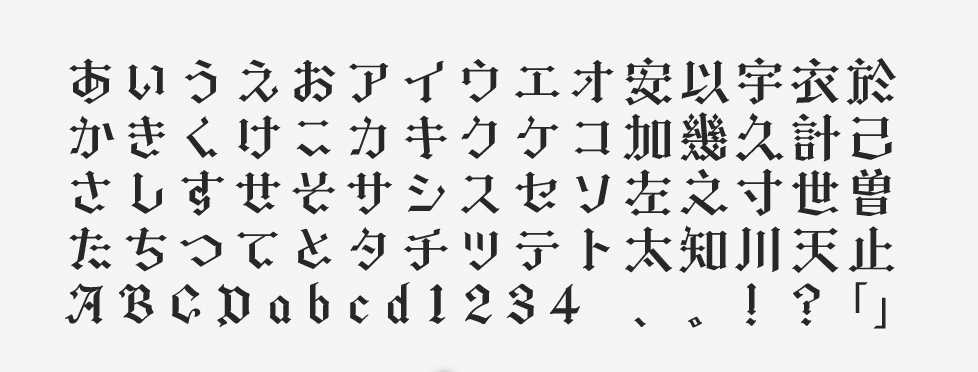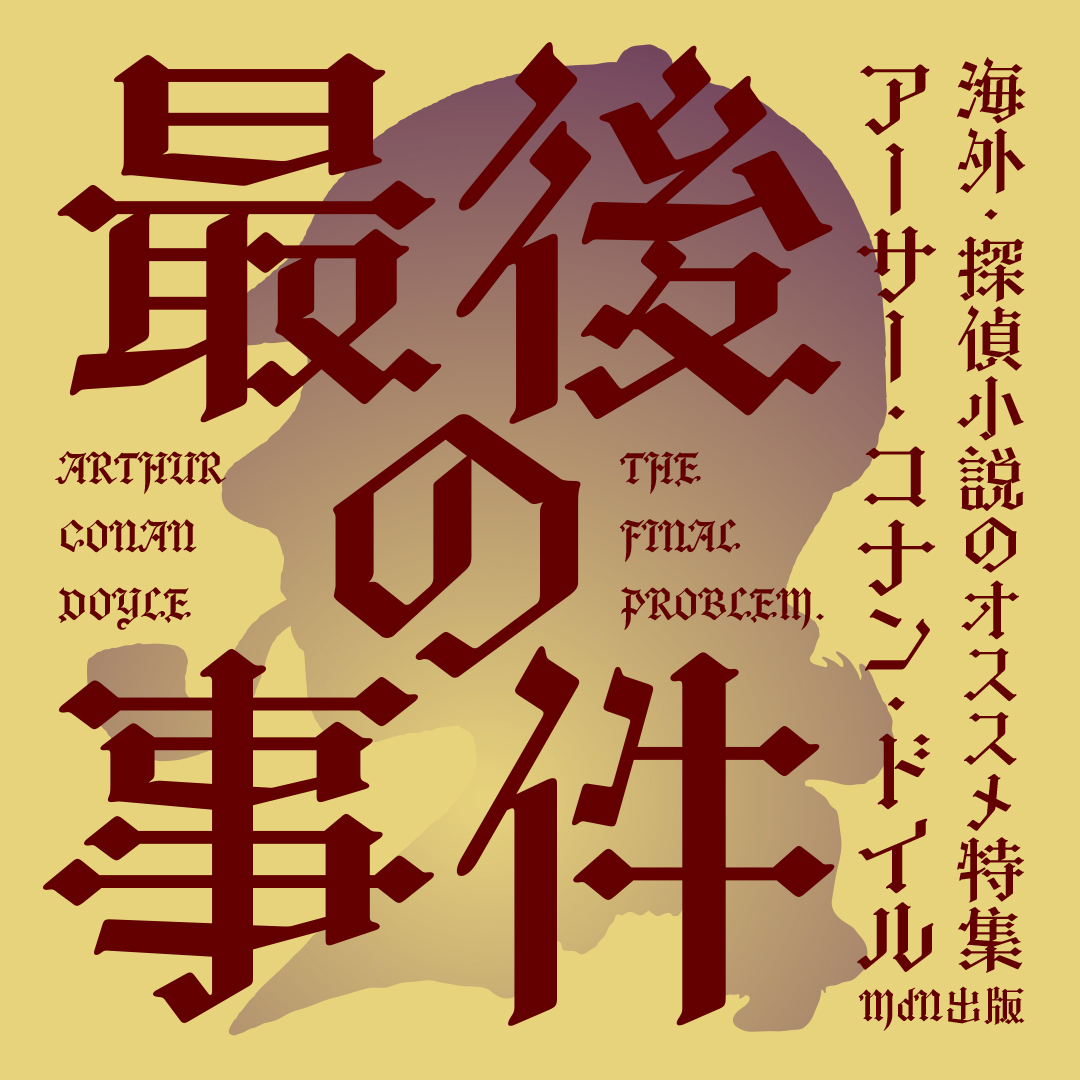
「オズ」について
オズは、タイプバンクブランドのかな書体・TBかナ-オズに漢字を追加して完成したフォントです。2022年秋の新書体として提供が開始されました。欧文にはブラックレターと呼ばれる書体の分類がありますが、そのエレメントにヒントを得てデザインされた装飾性の高さが特徴です。
「オズ」の特徴
オズは非常に個性的なフォントで、そのまま書籍のタイトルやコミック、パッケージのデザインなどにも使いやすい装飾性を備えています。インパクトが大きいため、表現したい世界観とマッチする媒体では抜群の効果を生み出せるでしょう。
文字の形は、平筆で書いたような直線的なストロークでありながらも、折り返しの角が丸く設計されています。硬くはなりすぎない絶妙なユニークさを醸し出すフォントです。
作例ではフォントそのものの世界観を生かし、シンプルにデザインしました。癖が強いフォントなので、さらにごちゃっとした装飾的なグラフィックと組み合わせても相乗効果を得られるでしょう。独特の雰囲気を演出しやすいフォントです。